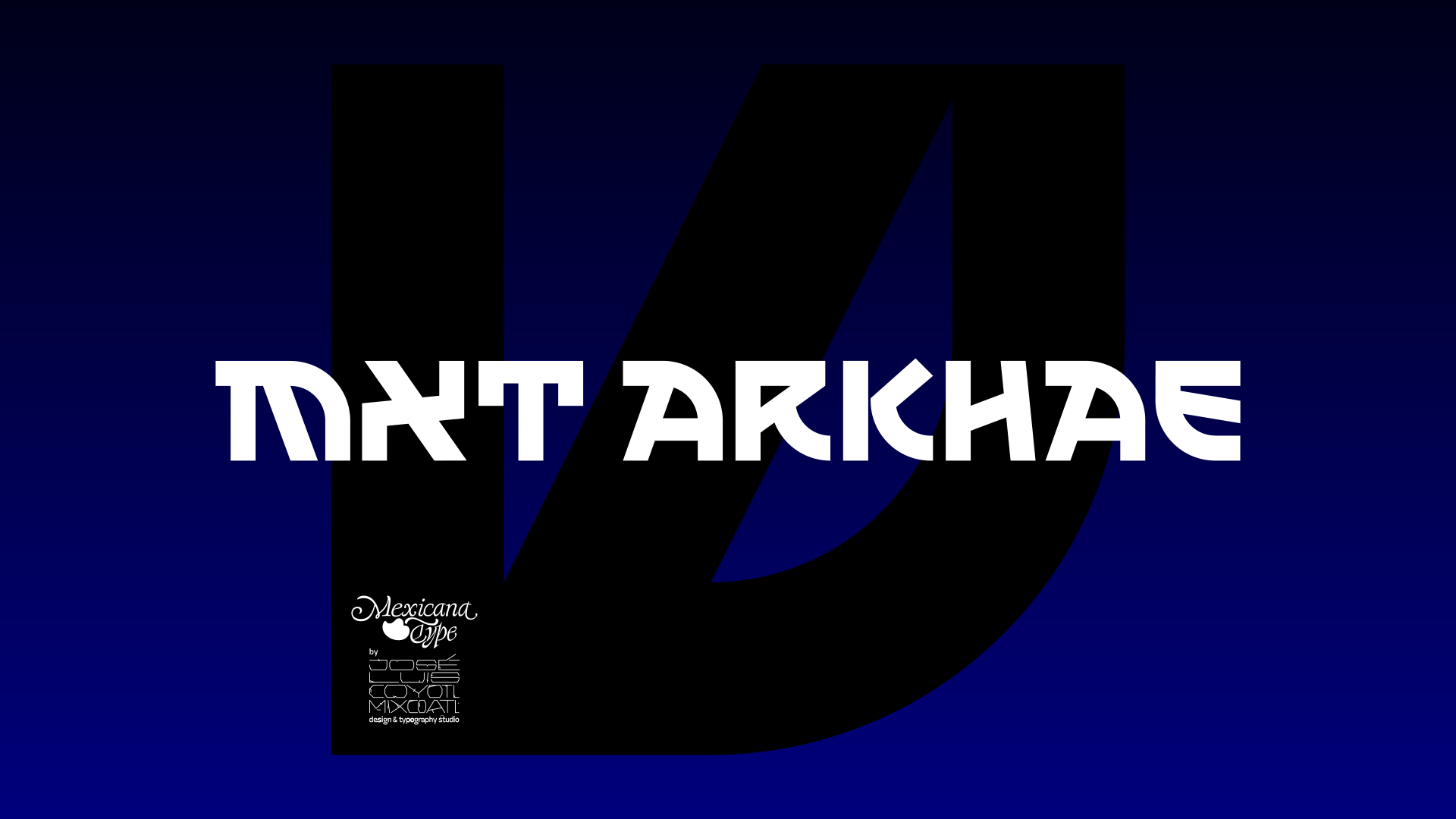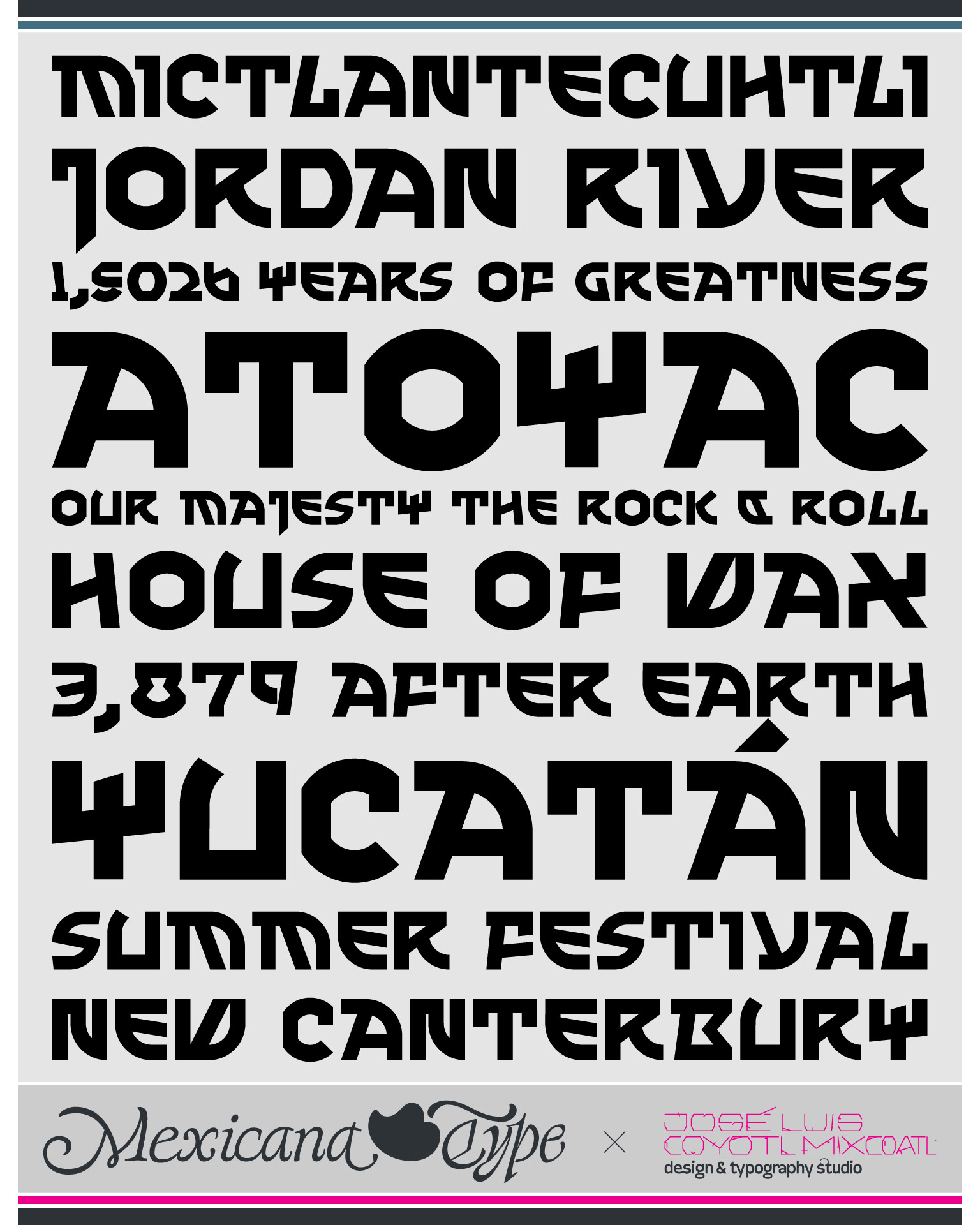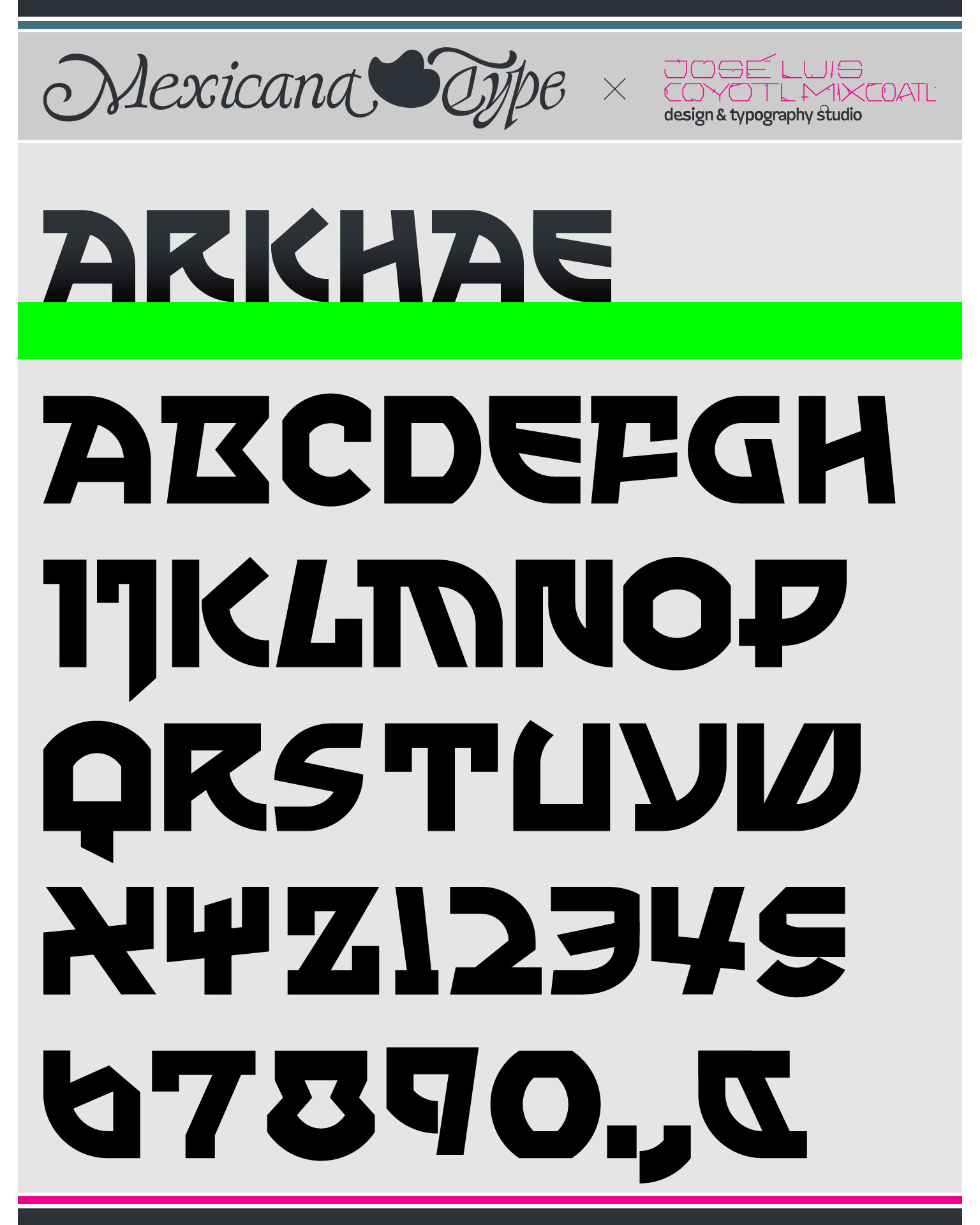
MxT Arkhae es una fuente que combina un perfil display pero tambien en cierto modo críptico. Desarrollada inicialmente para un proyecto custom type para ser grabada o moldeada en metal, por ello es que se desarrolló un set de caracteres básico en mayúsculas/altas, números y algunos signos de puntuación, pues inicialmente el proyecto contenía el uso de algunos pocos caracteres, y eventualmente se fueron complementando y expandiendo por cuenta propia dado el potencial de posibilidades expresivas que estaban generando, su asimetría y construcción con cierto aire modular le dá una textura tipográfica interesante y variada en formas y espacios blancos, contraformas y cuerpo que la hacen muy versátil.